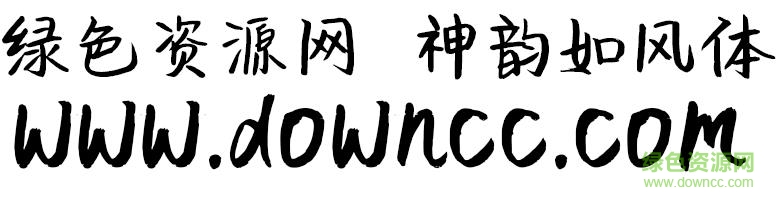
神韻如風(fēng)體字體
神韻如風(fēng)體ttf是一款神韻字體中十分不錯的字體,這款字體在使用的時候讓你感覺每一個字體都游走如風(fēng),十分不錯,讓你在使用這款字體的時候就如享受了一場寧靜的精神盛宴一樣,快來綠色資源網(wǎng)下載吧!
這款字體在風(fēng)格上給人一種十分舒適的體驗,擁有華麗的字體樣式結(jié)構(gòu),能夠讓你愛不釋手!